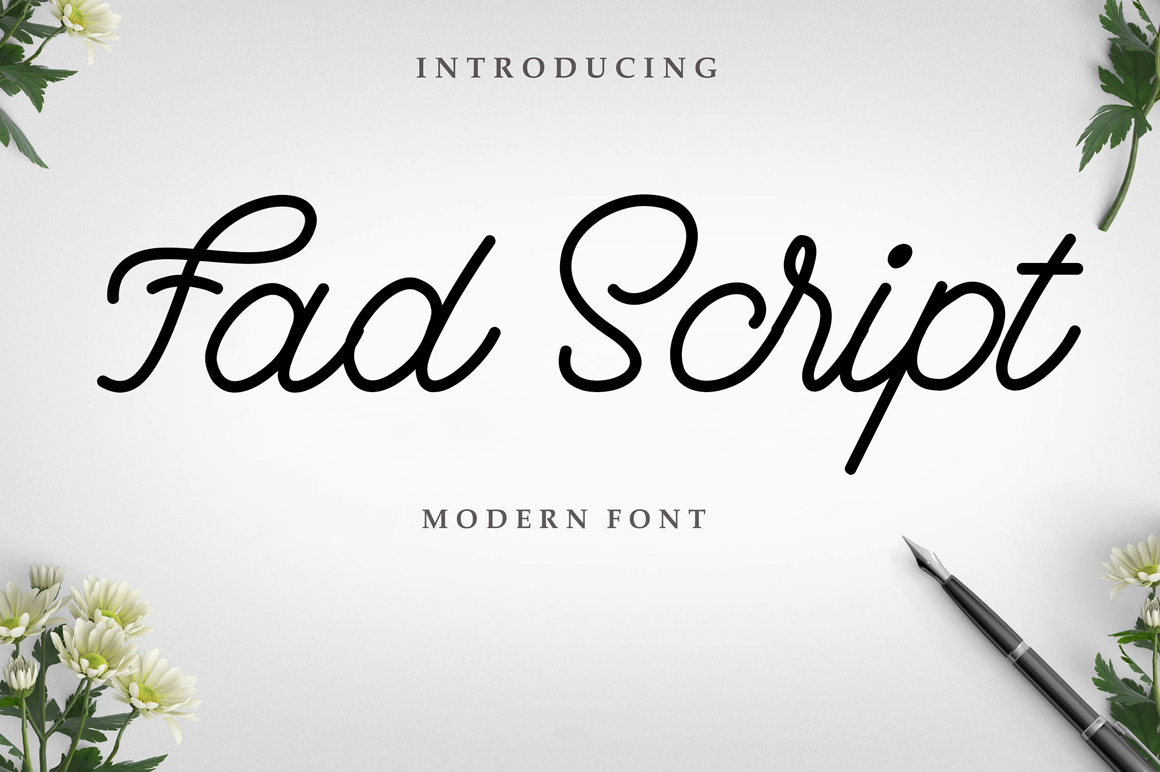
Introduzimos a Fad Script Font, uma nova tipografia script escrita a mão com seu próprio fluxo único e personalidade elegante. Desenhada e compartilhada por Magang Letterhend, essa fonte deixa sua marca sobre diversos ambientes de design gráfico, desde cartões-postais até revistas de moda ou capas de livros, passando por logotipos, rótulos de embalagens, cabeçalhos de sites e até mesmo roupas de moda. Perfeitamente adaptada a esses formatos, ela oferece uma dose de originalidade para seus projetos, tornando seu trabalho ainda mais especial. Fad Script é um elemento incrível para se incluir em sua coleção de fontes de design, garantindo que cada projeto seja único e de alta qualidade.